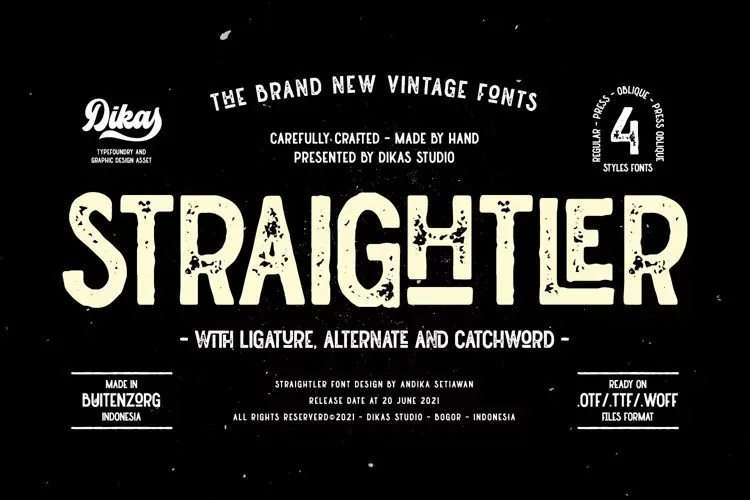
A Straightler Font é uma escolha perfeita para quem busca estilo retro e moderno ao mesmo tempo. Com quatro caracteres únicos que se destacam por sua textura e efeito gungareno, a Straightler adiciona um toque de vintage aos seus projetos digitais. Idealmente aplicável para várias funções de design gráfico, como tipografia, logotipos, embalagens de produtos, convites, citações, camisetas ou até mesmo materiais publicitários e panfletos, esta font dispõe de quatro estilos variados: regular, press, obliqúo e obliqúo press. Embora seja uma font básica em maiúsculas, a Straightler inclui alternativas de caracteres, ligação e traços que permitem transformar suas criações em algo realmente impecável. Não perca tempo, experimente essa font para dar um toque único ao seu próximo design!